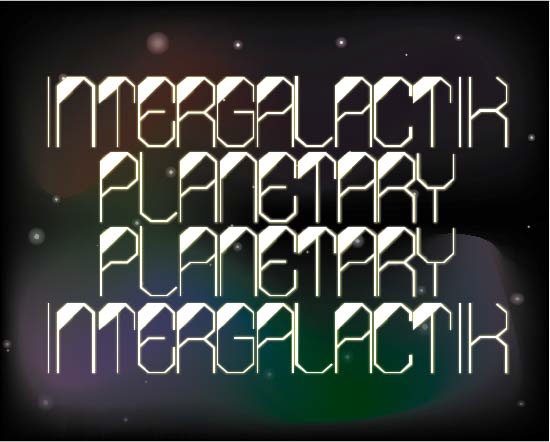
GALAXY TYPEFACE
Otra fuente basada en formas geométricas, resultado de una tarde de ocio y un papel cuadriculado...la canción intergalactic de los beastie boys vino a mi mente cuando la termine...